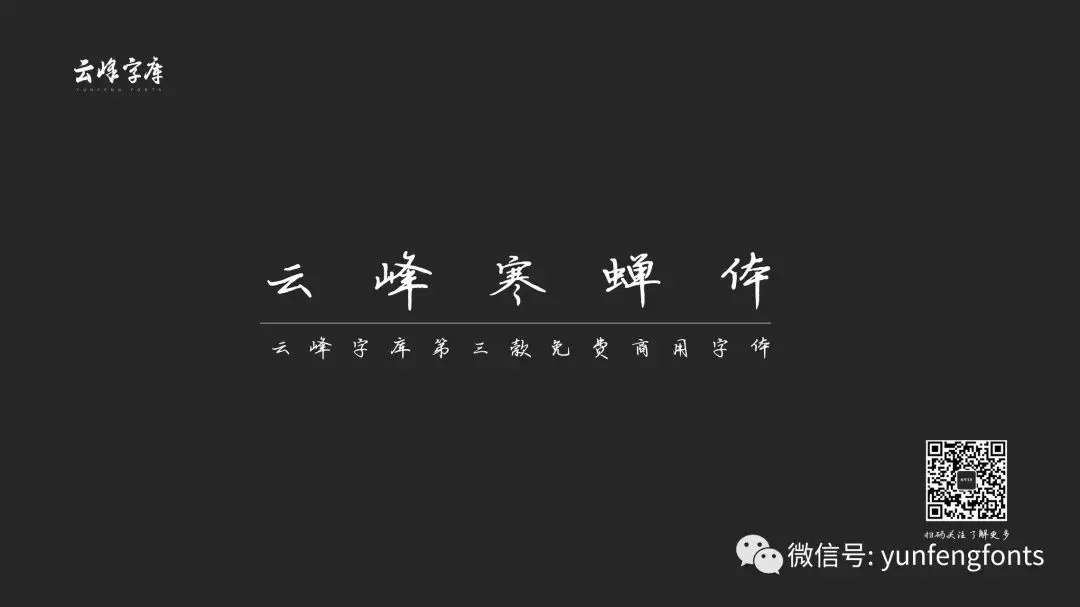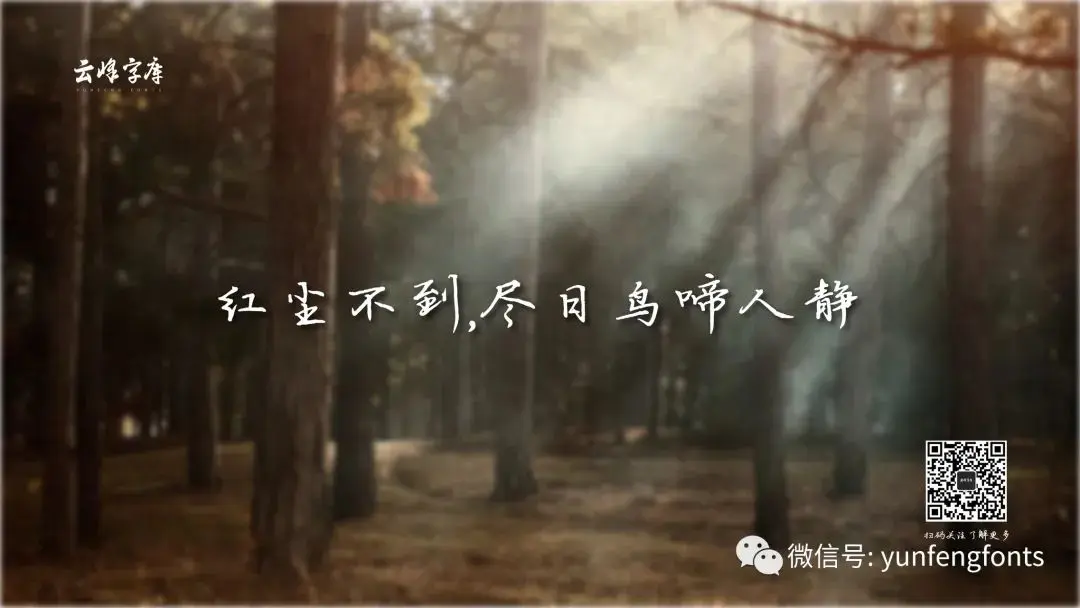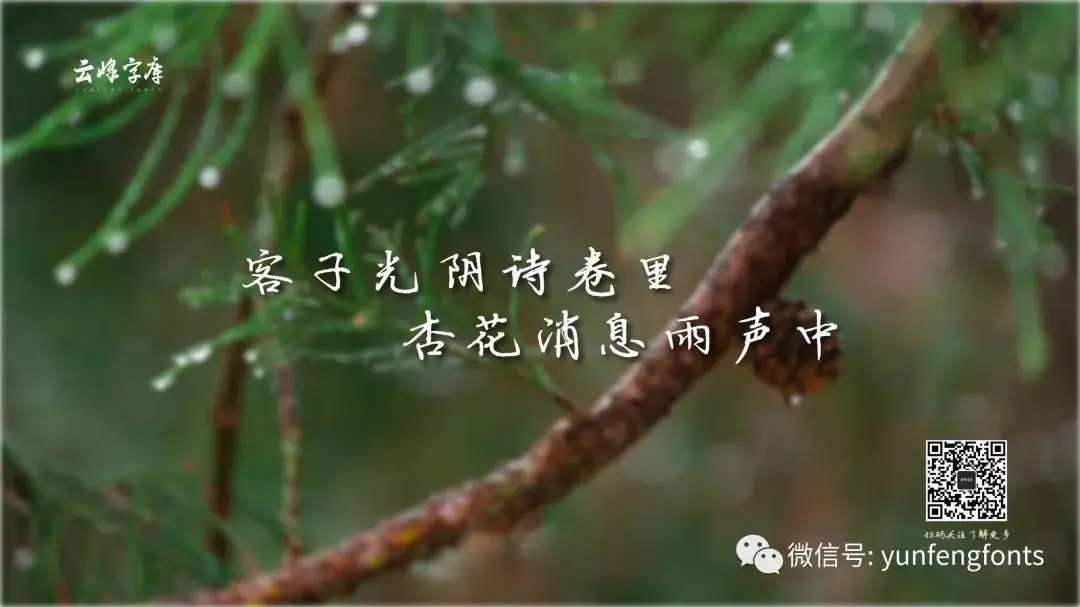
雲峰寒蟬體介紹
“雲峰寒蟬體”是一款一位美麗少女書寫的一款手寫字體,這款字很漂亮、耐看,非常適合閱讀、排版,可用於海報宣傳、書籍排版、裝訂、文案排版、自媒體視頻字幕等,整體閱讀性強,是一款好看且實用的硬筆書法字體,歡迎大家使用。在使用過程中如有發現錯別字及其它任何問題請反饋到QQ群205961668。